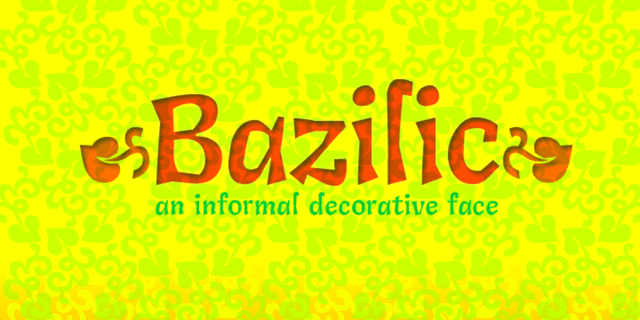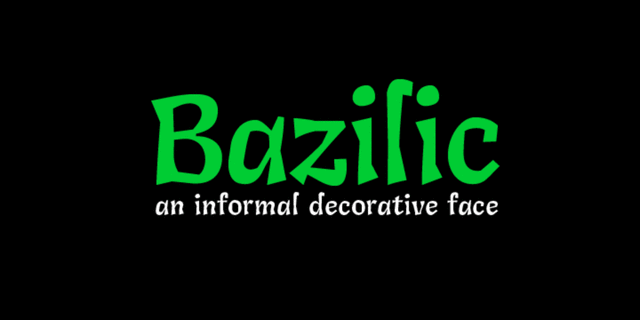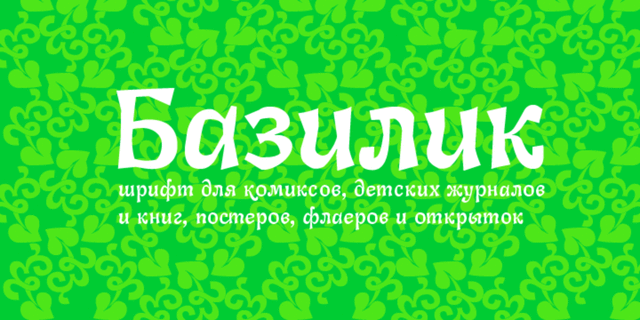
Базилик – это неформальный декоративный шрифт. Отлично смотрится в поздравительных открытках, детских книгах и журналах, на конфетах и пищевой упаковке, праздничных плакатах и рекламе. Базилик основан на неформальном леттеринге. Шрифт разработал Кирилл Ткачев в 2012 году.
Ассоциации c начертанием Bazilic RegularКачества и характер:
свежий, острый, смелый, самобытный, характерный, оригинальный, резкий, этничный, натуральный, традиционный, остроумный, колоритный, артистичный, динамичный, ремесленный, выразительный, крафтовый, художественный, приветливый, доброжелательный, дружелюбный, веселый, задорный, игривый, озорной, спелый, вкусный, детский, мультяшный, жаркий, южный, прикольный, дикий, живой, неотесанный, неровный, яркий, активный, летний, зеленый, ритмичный, четкий, ломаный, твердый, рукотворный, здоровый, сказочный, радостный, интересный, звонкий, гибкий, племенной, тропический, артизанальный, природный